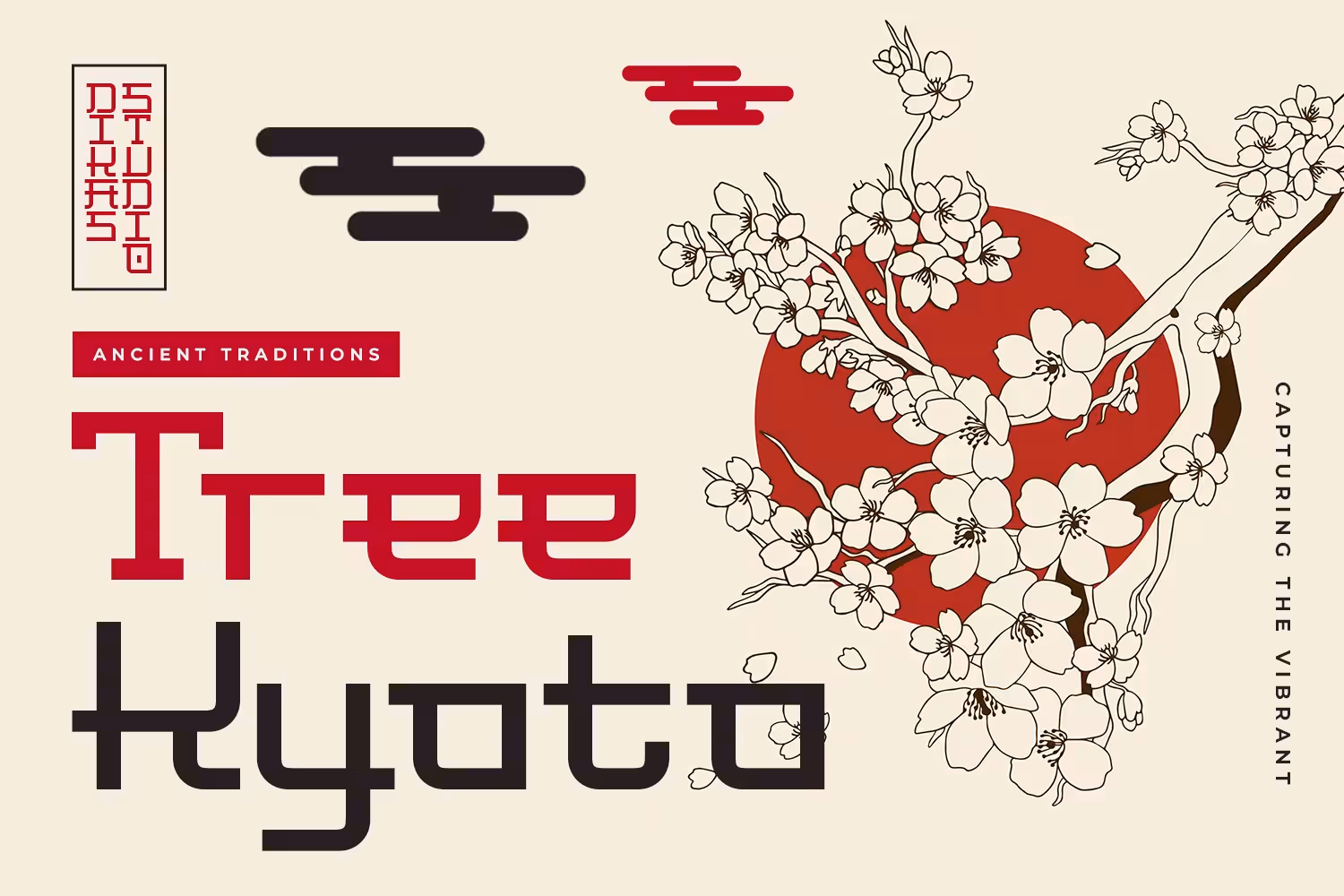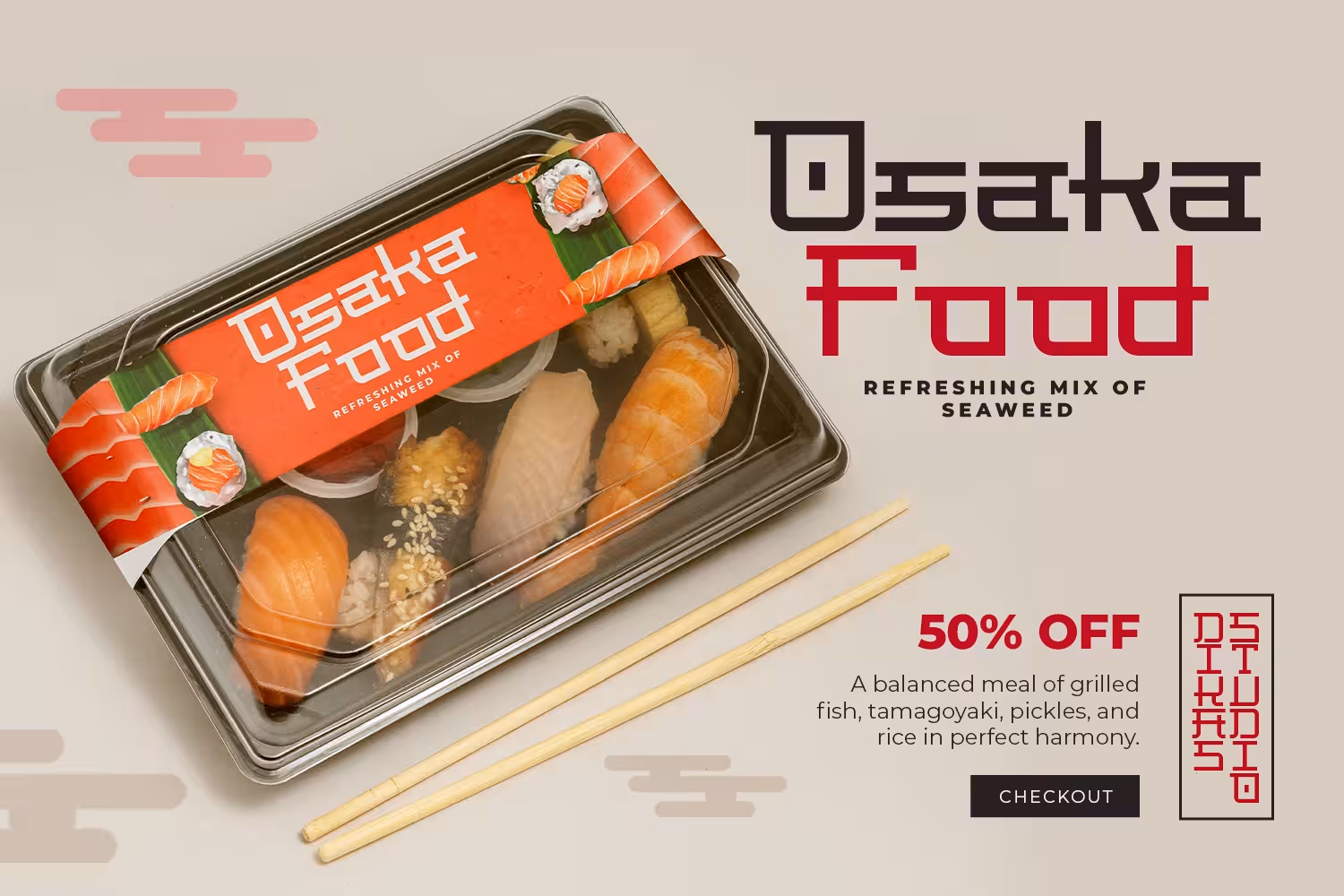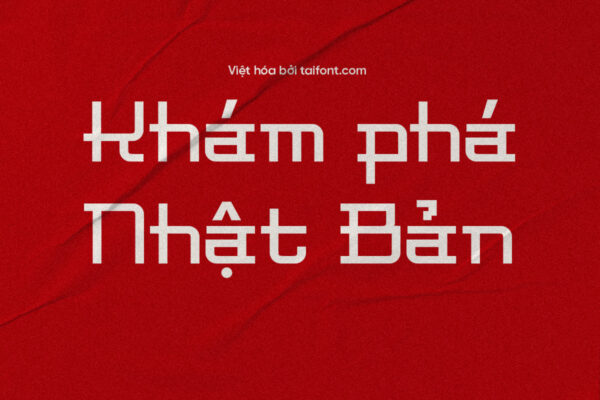
Giới thiệu về Font TF Neo Nippon Việt hóa
TF Neo Nippon Việt hóa là một font chữ độc đáo, được thiết kế lấy cảm hứng từ phong cách Nhật Bản, với những nét vẽ mềm mại, thanh thoát nhưng vẫn đầy ấn tượng. Font này mang đến vẻ ngoài tinh tế, gần gũi và một chút hoài niệm, gợi cảm giác về những quán ăn, cửa hàng truyền thống tại xứ sở hoa anh đào. Đây là lựa chọn lý tưởng để tạo điểm nhấn độc đáo và thu hút mọi ánh nhìn trong các thiết kế đòi hỏi sự thanh lịch và phong cách văn hóa riêng.
Với đặc điểm thiết kế độc đáo, đường nét sắc sảo và khả năng gợi cảm xúc mạnh mẽ về sự tinh tế, Neo Nippon là lựa chọn hoàn hảo cho các ấn phẩm liên quan đến văn hóa, ẩm thực Nhật Bản:
- Thiết kế ẩm thực và cà phê: Hoàn hảo để sử dụng cho logo nhà hàng, menu, bao bì sản phẩm, poster quảng bá món ăn của các quán ăn, quán cà phê, tiệm bánh mang phong cách Nhật Bản. Font này giúp món ăn trở nên hấp dẫn hơn, tạo cảm giác chuyên nghiệp, tinh tế và thu hút sự chú ý của thực khách.
- Thiết kế bao bì sản phẩm: Lý tưởng để sử dụng trên nhãn mác, bao bì của các sản phẩm có nguồn gốc từ Nhật Bản, hoặc các sản phẩm có phong cách tối giản, tinh tế. Font này giúp sản phẩm trở nên nổi bật và thu hút.
- Thiết kế nhận diện thương hiệu: Phù hợp cho logo, tagline hoặc bộ nhận diện thương hiệu của các công ty, doanh nghiệp muốn truyền tải sự tinh tế, uy tín và sự gần gũi, đặc biệt là các thương hiệu liên quan đến ẩm thực, du lịch, hoặc các sản phẩm mang phong cách Nhật Bản.
- Thiết kế in ấn và quảng cáo: Đảm bảo khả năng đọc tốt và tạo ấn tượng mạnh mẽ cho các ấn phẩm như brochure, catalogue, thiệp mời, bao bì sản phẩm mang phong cách Nhật Bản.
Với TF Neo Nippon Việt hóa, bạn có thể dễ dàng thổi hồn tinh tế, sang trọng và vẻ đẹp văn hóa Nhật Bản vào các thiết kế, tạo ra những sản phẩm không chỉ đẹp mắt mà còn đầy cảm xúc và sức hút đặc biệt.